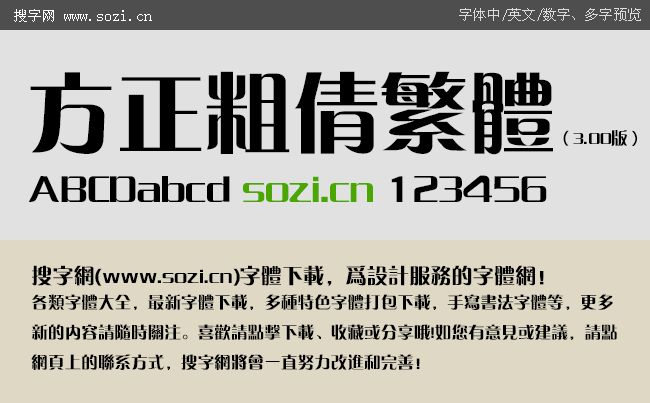
方正粗倩繁體
搜字網(wǎng)提供一款方正粗倩繁體中文字體下載,該字體效果非常出眾,字形端正大方得體,一筆一畫筆鋒犀利,適合應(yīng)用于廣告設(shè)計(jì)、名片設(shè)計(jì)、包裝印刷、產(chǎn)品設(shè)計(jì)等應(yīng)用。
• 風(fēng)格類別: 倩體